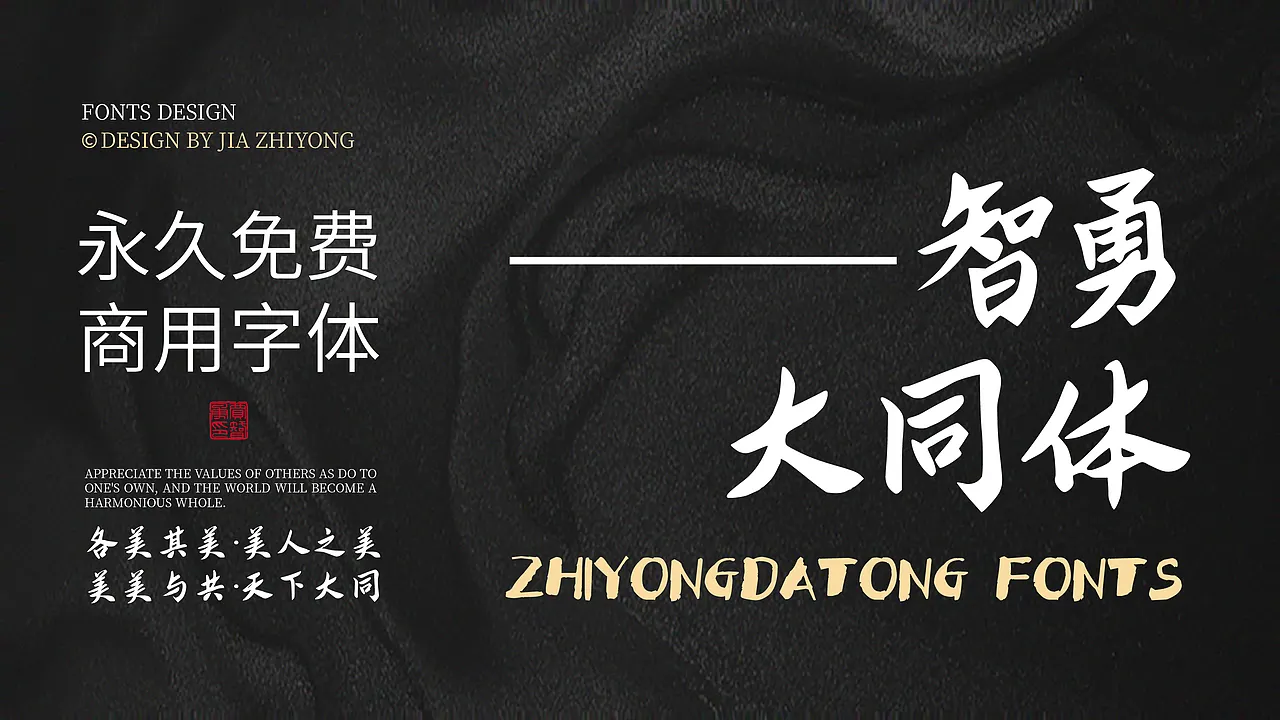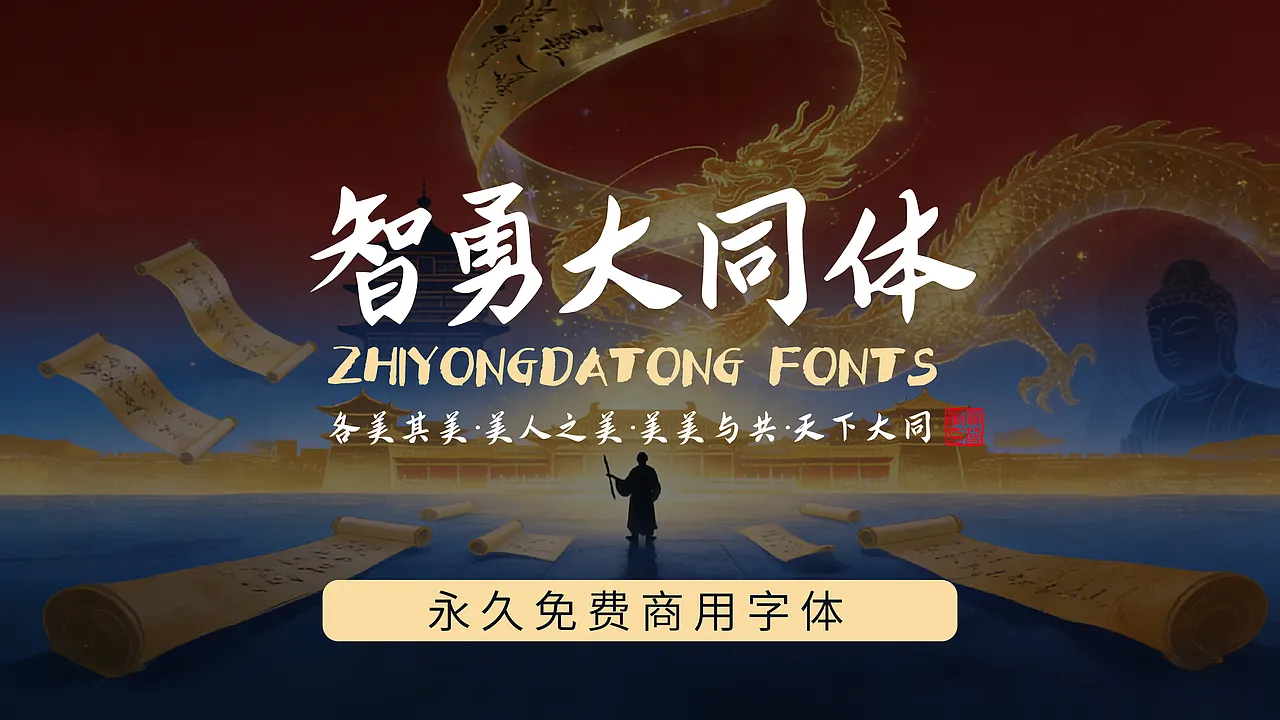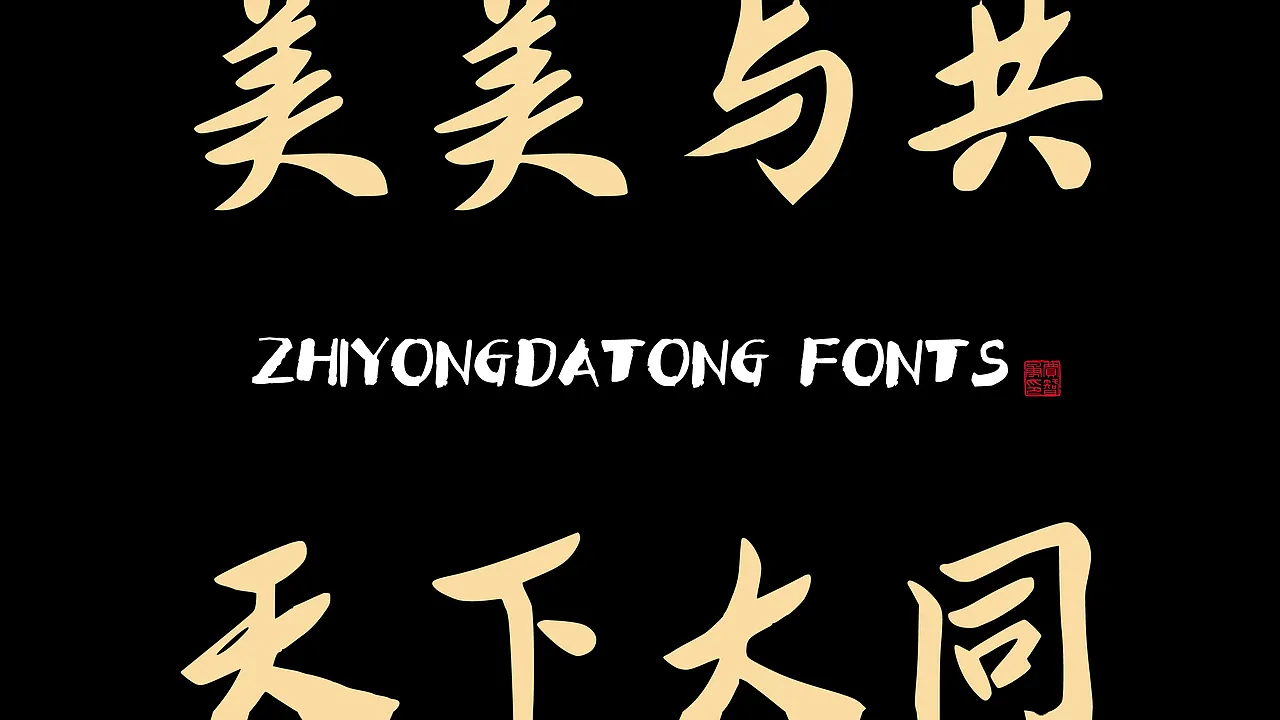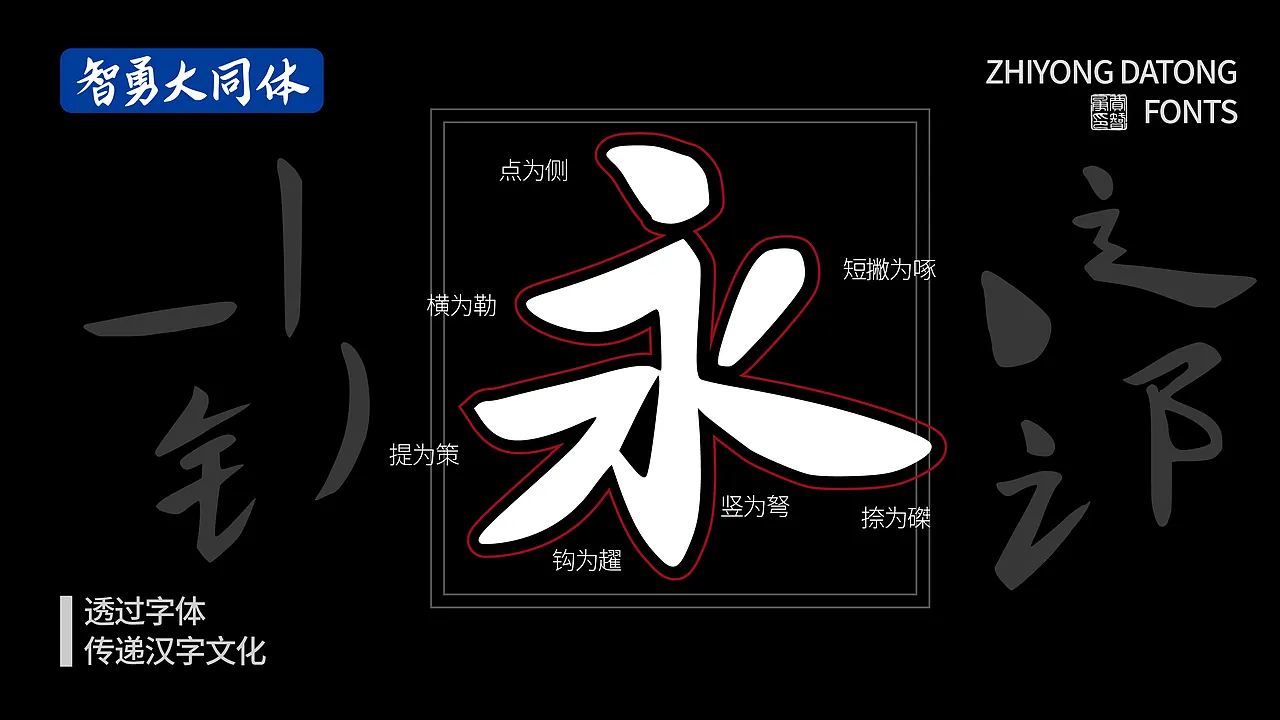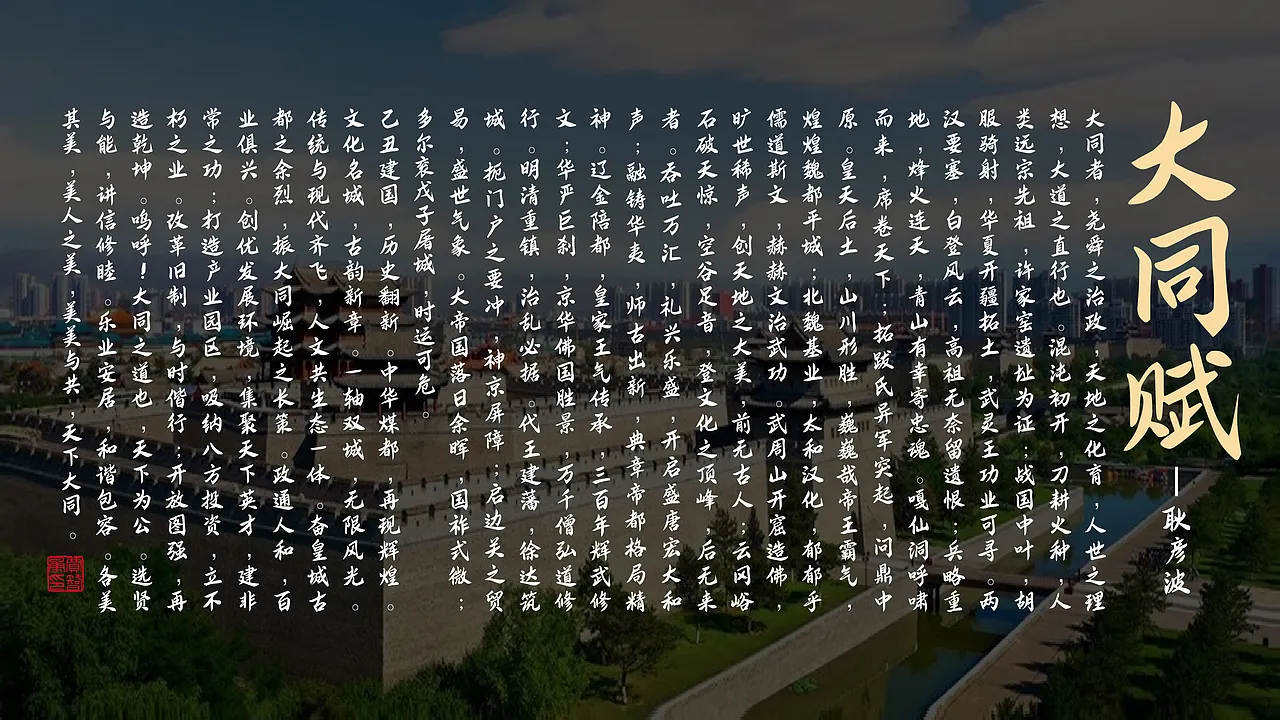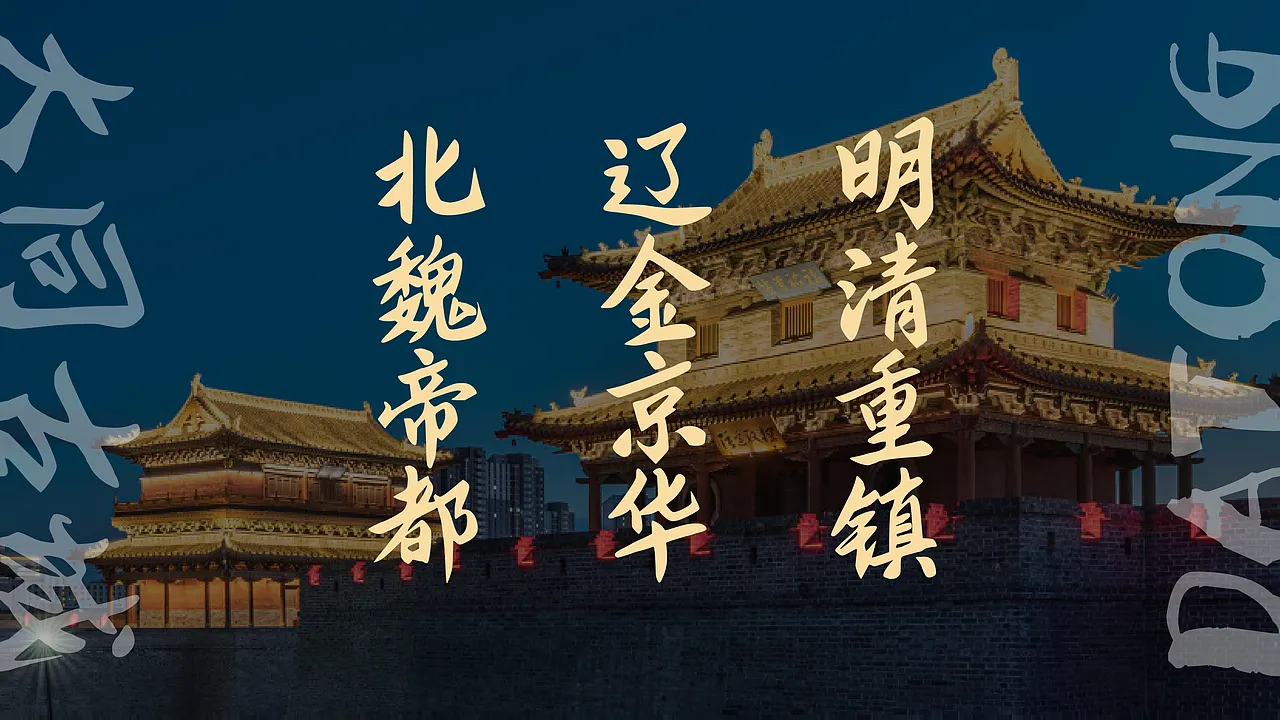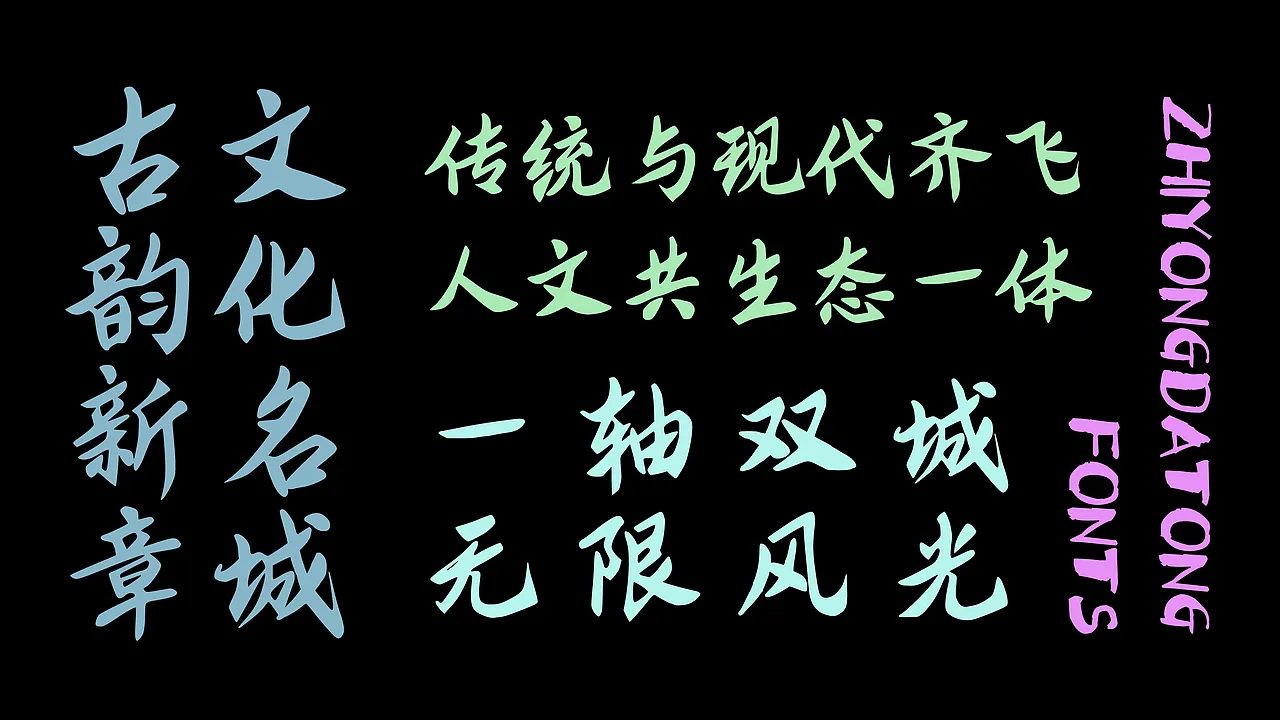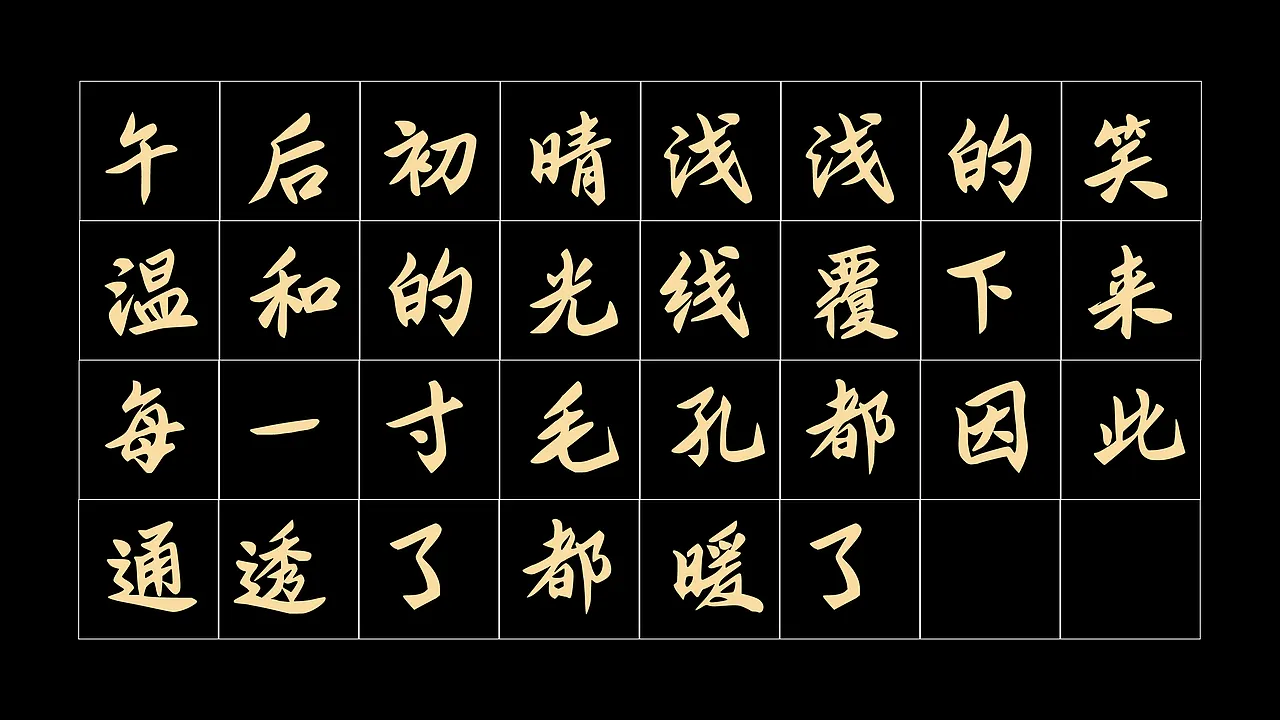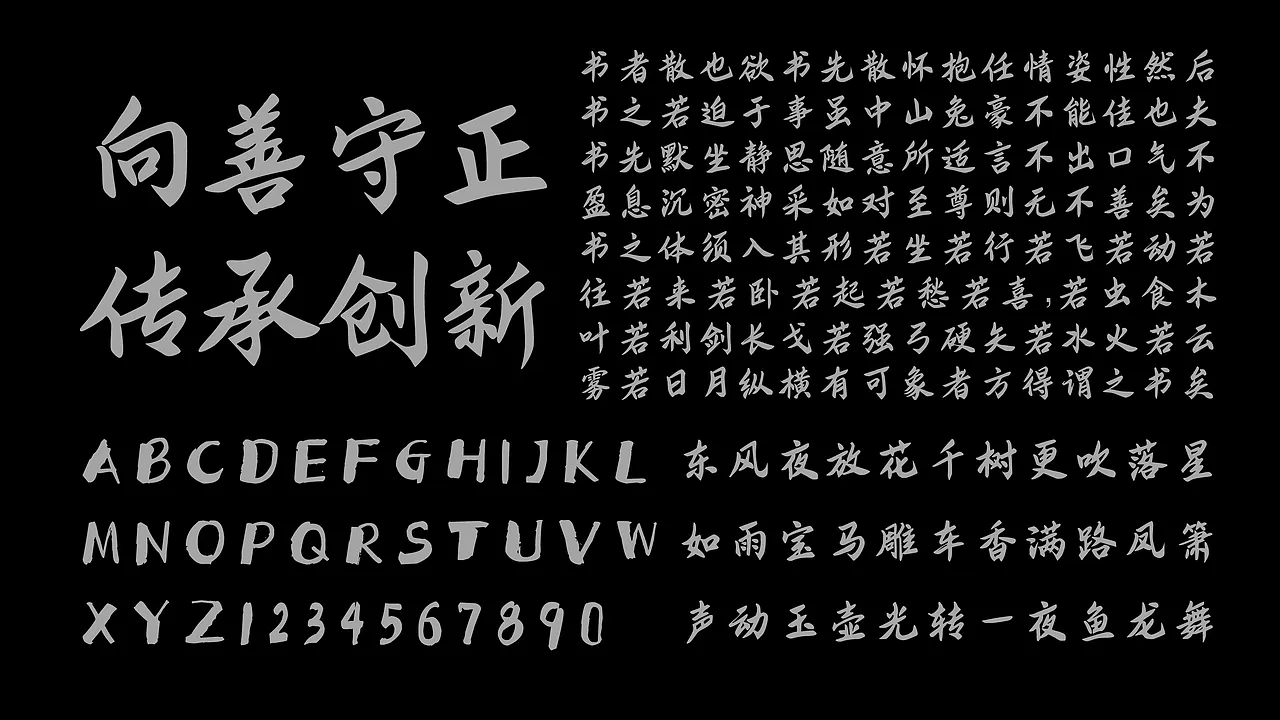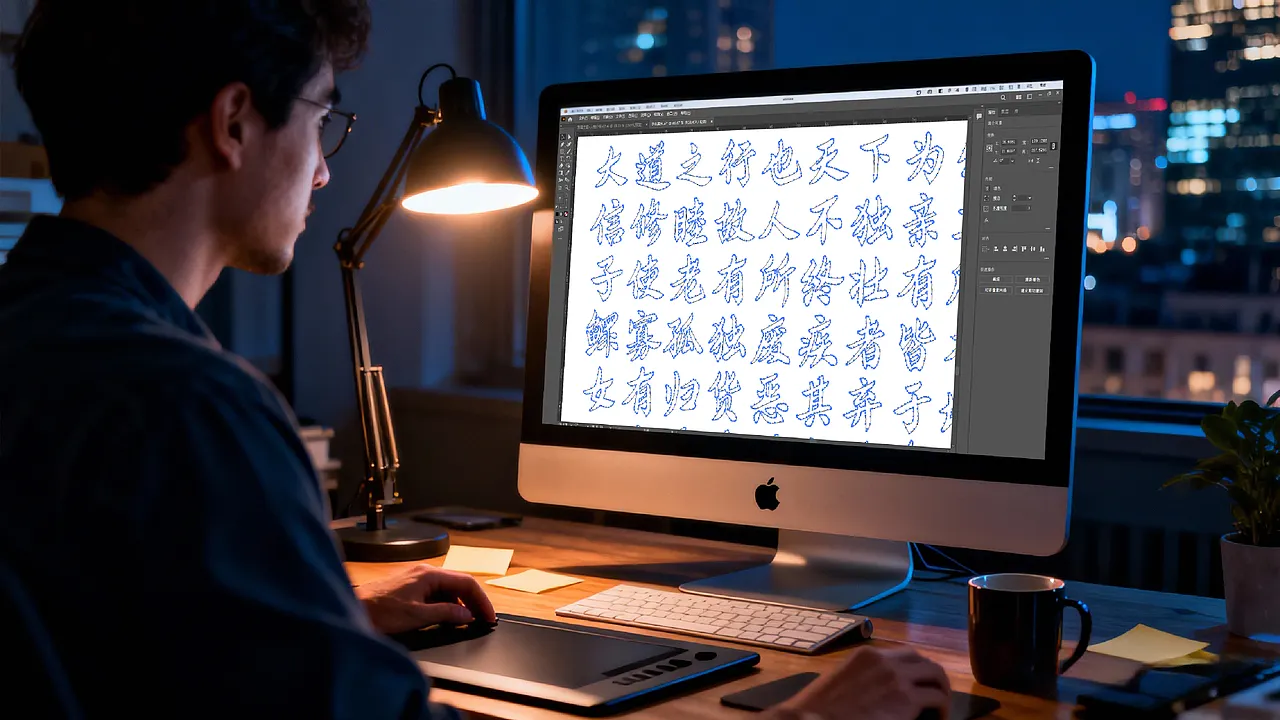
新款字体,历时两年多,6763个常用汉字,从最初的手写草稿,到AI辅助生成的初步字库,再到如今逐字精修的成品,每一个笔画都浸润着我对家乡的热爱,对字体设计的热爱,以及对“天下大同”理念的执着追求。
智勇大同体,经过700天的匠心之旅,现在提供给大家,
字如其名:三重深意
智勇 :是我的名字,贾智勇,它代表着这款字体的起点,是我个人意识与字体的投射。
大同:我的家乡山西大同,这座承载着北魏、辽金等朝代辉煌历史的城市,为我提供了无尽的设计灵感。
大同:更取“天下大同”之意,
各美其美,美人之美,美美与共,天下大同。
希望这款免费商用的字体可以为更多人提供设计的温暖与便利,让设计的力量惠及天下。
智勇大同体字体宣传图,永久免费商用,由贾志勇设计,传达各美其美、天下大同的理念。-刊刻Kntuk
智勇大同体(ZHIYONGDATONG FONTS)永久免费商用字体,中国风龙与卷轴背景,含“各美其美·美人之美·美美与共·天下大同”-刊刻Kntuk
展示“ZHIYONGDATONG FONTS”字体效果,包含“美美与共”与“天下大同”字样。-刊刻Kntuk
智勇大同体字体展示永字八法,解析点为侧、横为勒、竖为弩、钩为趯、提为策、短撇为啄、捺为磔,透过字体传递汉字文化-刊刻Kntuk
耿彦波《大同赋》全文配大同城市风景,内容涵盖大同历史文脉与现代发展愿景-刊刻Kntuk
大同古城夜景,展示其北魏帝都、辽金京华、明清重镇的历史定位-刊刻Kntuk
古韵新章 文化名城 传统与现代齐飞 人文共生态一体 一轴双城 无限风光 ZHIYONGDATONG FONTS-刊刻Kntuk
午后初晴浅浅的笑,温和的光线覆下,每一寸毛孔都因此通透了都暖了-刊刻Kntuk
展示书法字体字符集,含“向善守正 传承创新”、《笔阵图》选段、英文字母数字及辛弃疾词句。-刊刻Kntuk
一名戴眼镜的男子在夜间使用数位板和电脑进行中文书法创作,屏幕显示《大道之行也》的蓝色字迹-刊刻Kntuk